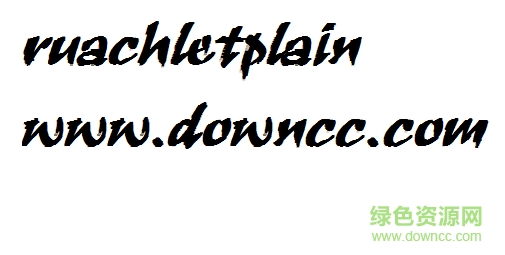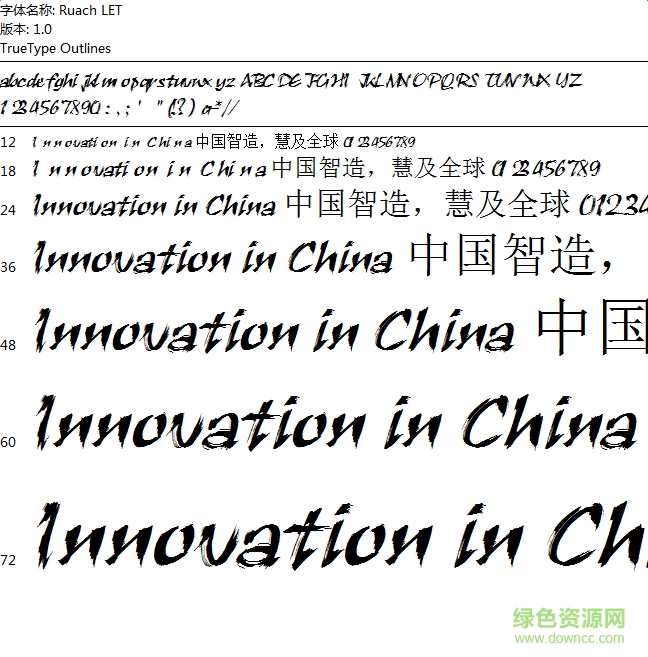
ruachletplain字體是一款英文系列字體,字體以粗黑整齊大方著稱,筆畫特點十足,十分酷炫,非常好看,感興趣的朋友歡迎到綠色資源網(wǎng)下載體驗!
ruachletplain字體是一款應(yīng)用于藝術(shù)設(shè)計方面的簡體英文字體,該字體筆畫粗壯,尾部的甩尾有力且有豐富的筆觸細(xì)節(jié),大字效果突出且引人注目;并且最大程度還原作者書寫字形,細(xì)節(jié)表現(xiàn)完整,且字庫完整,可以廣泛應(yīng)用于名片設(shè)計、新聞媒體、宣傳海報、ppt、影視制作以及內(nèi)容用字等領(lǐng)域。
ruachletplain英文字體是一類手寫字體,字體比較時尚潮流,整體效果非??犰?,深受廣大年輕人喜愛!